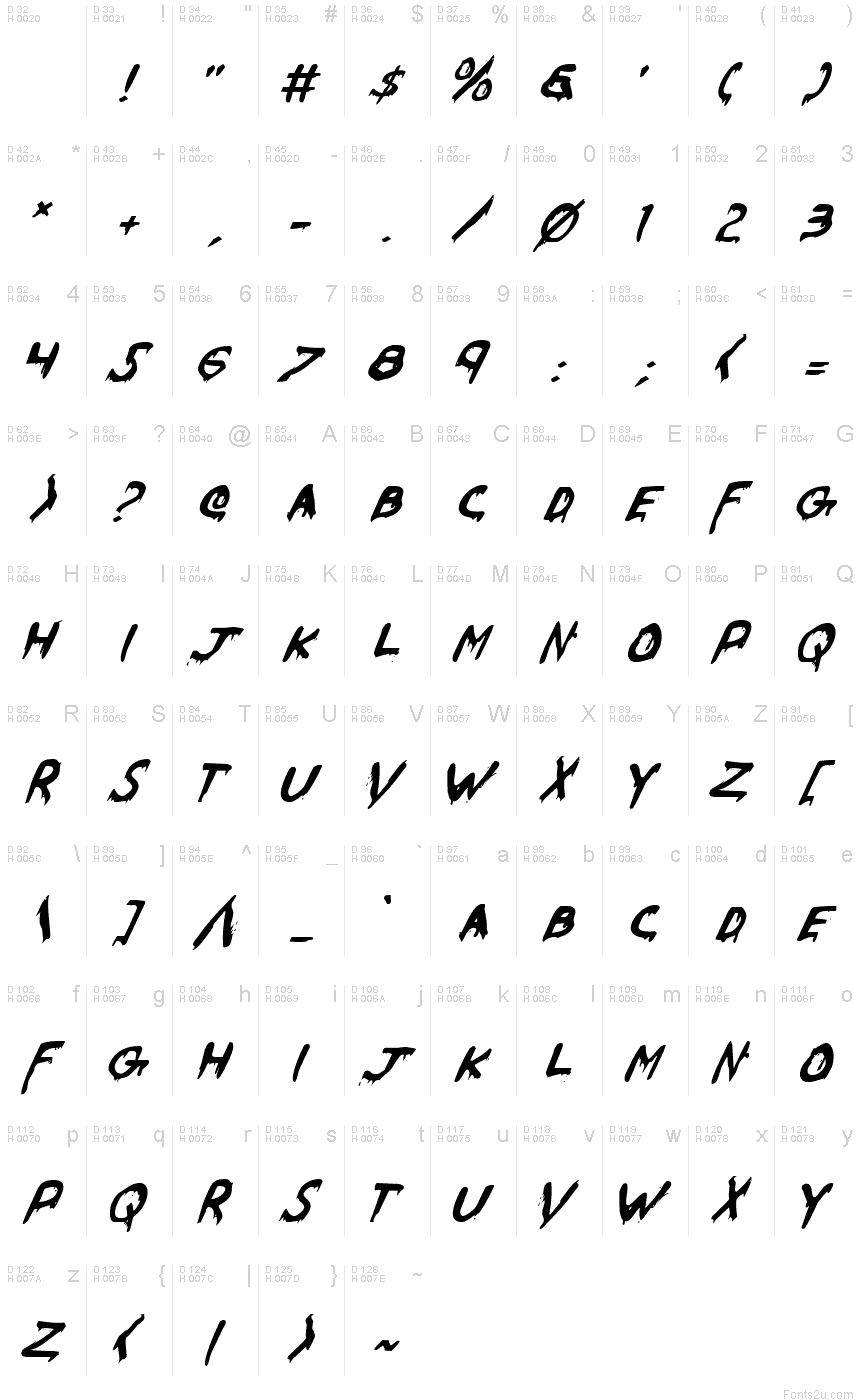
Were-Beast Italic od Iconian Fonts to darmowy horrorowy font typu display, który przypomina pociągnięcia pędzlem i charakteryzuje się dzikim pochyleniem w przód. Poszarpane cięcia, zwężające się linie i sporadyczne elementy przypominające ściekającą farbę nadają literom wygląd szybkich zadrapań pazurami, podczas gdy szerokie, zamaszyste formy sprawiają, że ten groźny klimat pozostaje czytelny i graficzny, zamiast być przesadnie ozdobnym.
Jego poszarpana, malarska sylwetka tworzy wrażenie niespokojnego ruchu na plakatach horrorów i logotypach gier. Użyj tego darmowego fontu do oznaczeń nawiedzonych atrakcji, opakowań na Halloween czy agresywnego mercha zespołów muzycznych, gdzie jego surowa, „pocięta” faktura może przywoływać skojarzenia ze śladami pazurów, potworami i mroczną estetyką bez konieczności dodawania jakichkolwiek ozdobników.